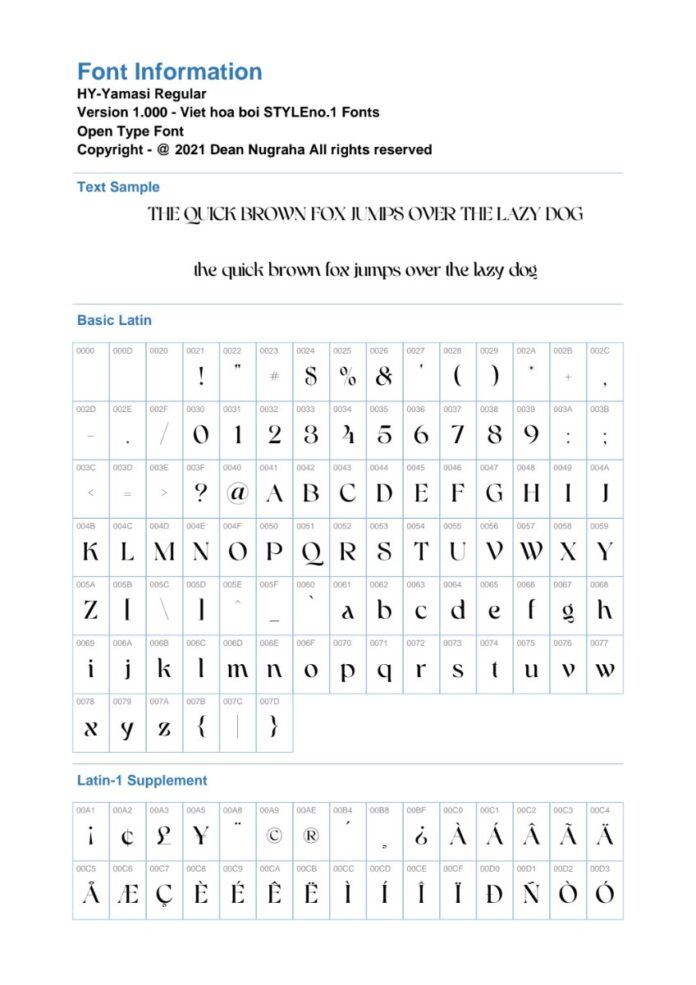
Font HY-Yamasi: Nét Cổ Điển Hiện Đại
Font HY-Yamasi: Nét Cổ Điển Hiện Đại. Khám phá font chữ HY-Yamasi, một lựa chọn hoàn hảo cho thiết kế mang phong cách cổ điển và sang trọng. Font này phù hợp cho tiêu đề, logo và các ấn phẩm đòi hỏi sự tinh tế, đẳng cấp.
Trong thế giới thiết kế đồ họa, việc lựa chọn một font chữ phù hợp có thể tạo nên sự khác biệt lớn cho tác phẩm của bạn. Font HY-Yamasi là một trong những lựa chọn đáng giá, mang đến sự kết hợp hài hòa giữa nét cổ điển và hiện đại. Với thiết kế độc đáo, font chữ này không chỉ thu hút ánh nhìn mà còn truyền tải thông điệp một cách mạnh mẽ và tinh tế.
Giới Thiệu Font HY-Yamasi
Font HY-Yamasi được thiết kế bởi Dean Nugraha, phát hành vào năm 2021. Đây là một font chữ OpenType với phiên bản 1.000, thuộc họ font Viet hoa boi STYLEno.1 Fonts. HY-Yamasi nổi bật với các ký tự La-tinh cơ bản và bổ sung La-tinh-1, hỗ trợ đa dạng ngôn ngữ và ứng dụng.
Với các đường nét thanh mảnh, có chân (serif) và độ tương phản cao giữa nét dày và nét mỏng, HY-Yamasi gợi nhớ đến phong cách typography cổ điển, thường thấy trong các ấn phẩm in ấn từ thế kỷ trước. Tuy nhiên, sự tinh chỉnh trong từng chi tiết giúp font này vẫn giữ được vẻ hiện đại, dễ đọc và ứng dụng trong nhiều ngữ cảnh thiết kế ngày nay.
Đặc Điểm Nổi Bật Của Font
• Phong cách cổ điển pha hiện đại: Sự kết hợp giữa nét truyền thống và hơi thở đương đại tạo nên vẻ đẹp độc đáo.
• Độ dễ đọc cao: Dù mang phong cách cổ điển, các ký tự được thiết kế rõ ràng, giúp người đọc dễ dàng tiếp nhận thông tin.
• Hỗ trợ đa ngôn ngữ: Bao gồm các ký tự La-tinh cơ bản và bổ sung La-tinh-1, phù hợp cho nhiều dự án quốc tế.
• Tính linh hoạt: Có thể sử dụng cho nhiều mục đích khác nhau, từ tiêu đề, logo đến nội dung văn bản ngắn.
Ứng Dụng Của Font HY-Yamasi Trong Thiết Kế
Font HY-Yamasi là lựa chọn lý tưởng cho các nhà thiết kế muốn tạo ra những sản phẩm mang tính nghệ thuật cao, sang trọng và có chiều sâu. Dưới đây là một số ứng dụng phổ biến:
Thiết Kế Logo và Nhận Diện Thương Hiệu
Với vẻ ngoài tinh tế và độc đáo, HY-Yamasi rất phù hợp để thiết kế logo cho các thương hiệu cao cấp như thời trang, trang sức, mỹ phẩm, nhà hàng sang trọng hoặc các dịch vụ chuyên nghiệp. Font chữ này giúp truyền tải sự uy tín, đẳng cấp và sự chú trọng đến từng chi tiết của thương hiệu.
Ấn Phẩm In Ấn và Quảng Cáo
Các ấn phẩm như poster, brochure, thiệp mời, bìa sách hay tạp chí sẽ trở nên ấn tượng hơn khi sử dụng HY-Yamasi cho tiêu đề hoặc các đoạn văn bản quan trọng. Font chữ này mang lại cảm giác sang trọng, cổ điển nhưng vẫn rất thu hút và hiện đại.
Thiết Kế Website và Giao Diện Người Dùng
Trong thiết kế web, HY-Yamasi có thể được dùng cho các tiêu đề chính, menu điều hướng hoặc các phần nội dung đặc biệt để tạo điểm nhấn. Sự rõ ràng và tính thẩm mỹ của font giúp nâng cao trải nghiệm người dùng, đặc biệt trên các trang web có phong cách tối giản, sang trọng.
Hướng Dẫn Sử Dụng Font HY-Yamasi Hiệu Quả
Để tận dụng tối đa vẻ đẹp của Font HY-Yamasi, bạn cần lưu ý một số điểm sau:
• Kết hợp với font chữ khác: HY-Yamasi thường phát huy tối đa vẻ đẹp khi được kết hợp với các font sans-serif đơn giản, hiện đại để tạo sự cân bằng và dễ đọc cho nội dung chính.
• Kích thước và khoảng cách: Điều chỉnh kích thước và khoảng cách giữa các ký tự (kerning) một cách hợp lý để đảm bảo tính thẩm mỹ và dễ đọc, đặc biệt là khi sử dụng cho tiêu đề lớn.
• Màu sắc: Font này thường phù hợp với các bảng màu trầm, sang trọng hoặc các màu sắc tương phản mạnh để tạo điểm nhấn.
Font HY-Yamasi phù hợp với loại thiết kế nào?
Font HY-Yamasi rất phù hợp cho các thiết kế mang phong cách cổ điển, sang trọng như logo thương hiệu cao cấp, tiêu đề ấn phẩm in ấn, thiệp mời, bìa sách hoặc các dự án đòi hỏi sự tinh tế và đẳng cấp.
Font HY-Yamasi có hỗ trợ tiếng Việt không?
Font HY-Yamasi thuộc họ font Viet hoa boi STYLEno.1 Fonts, nên có khả năng hỗ trợ tiếng Việt, giúp bạn dễ dàng sử dụng trong các dự án có nội dung tiếng Việt.